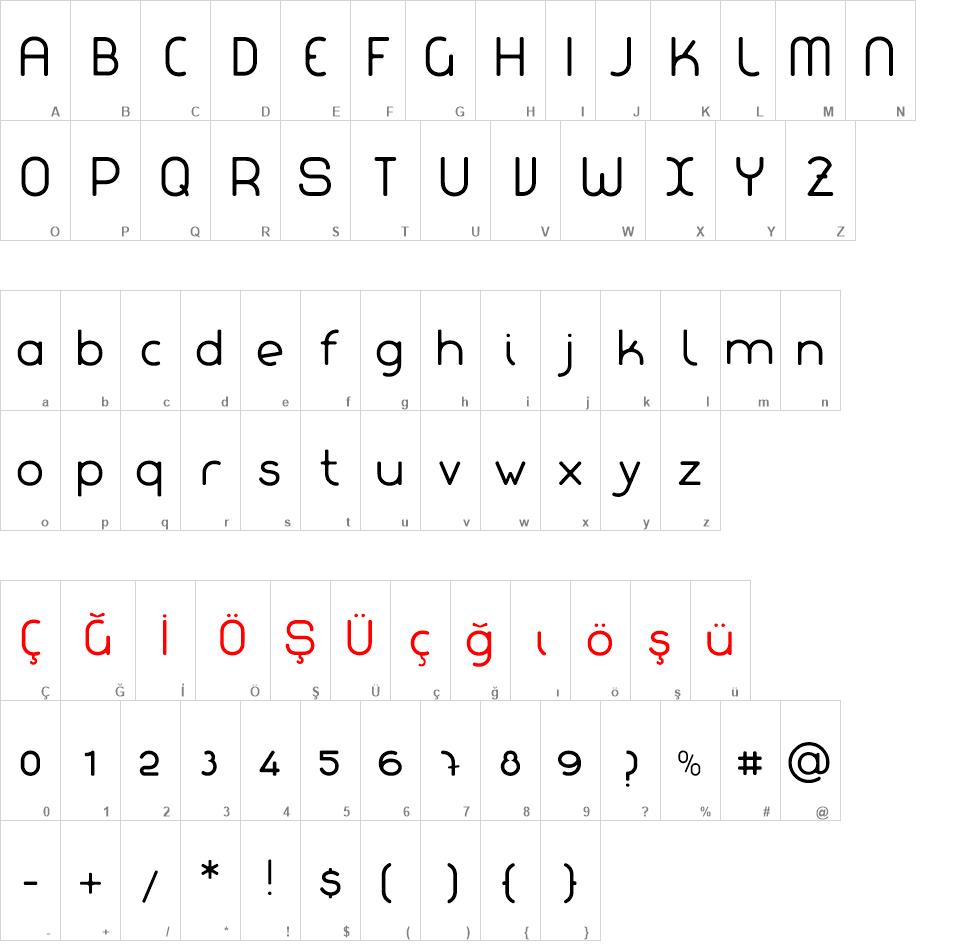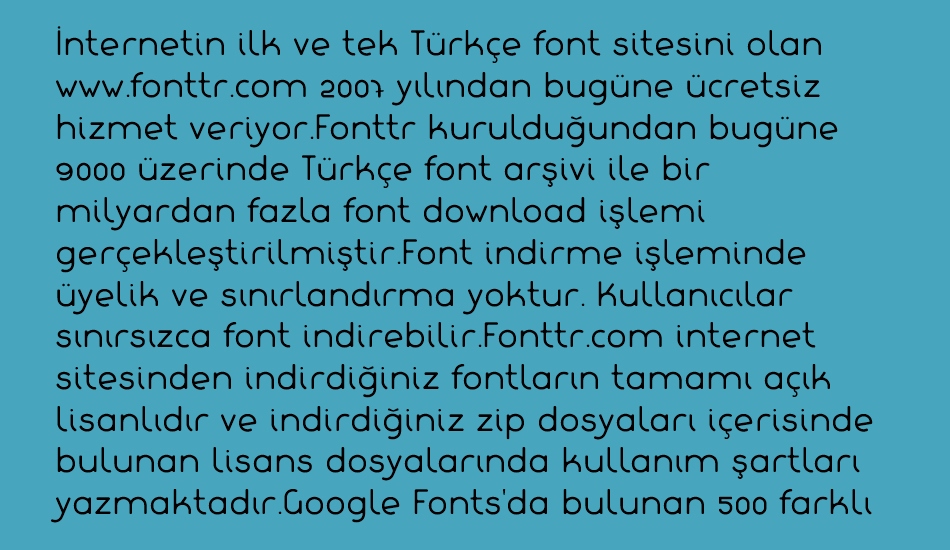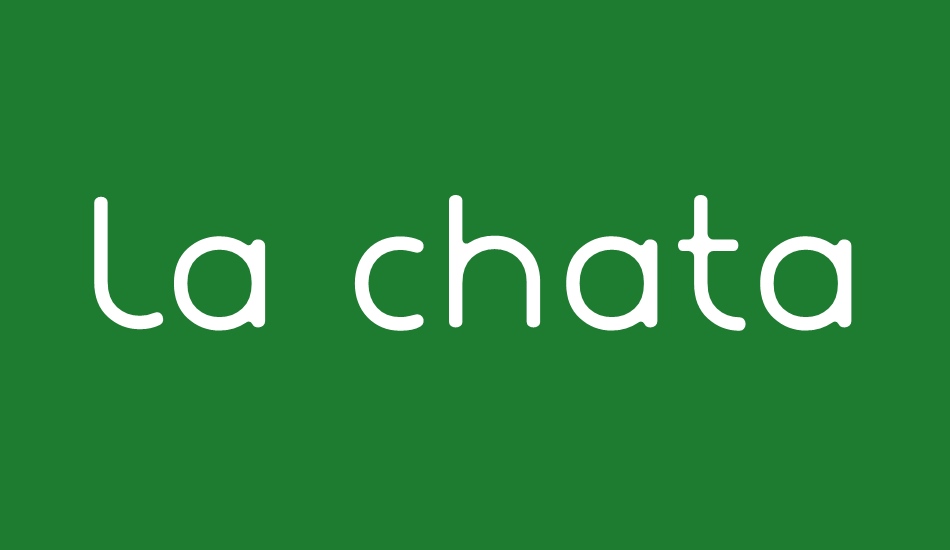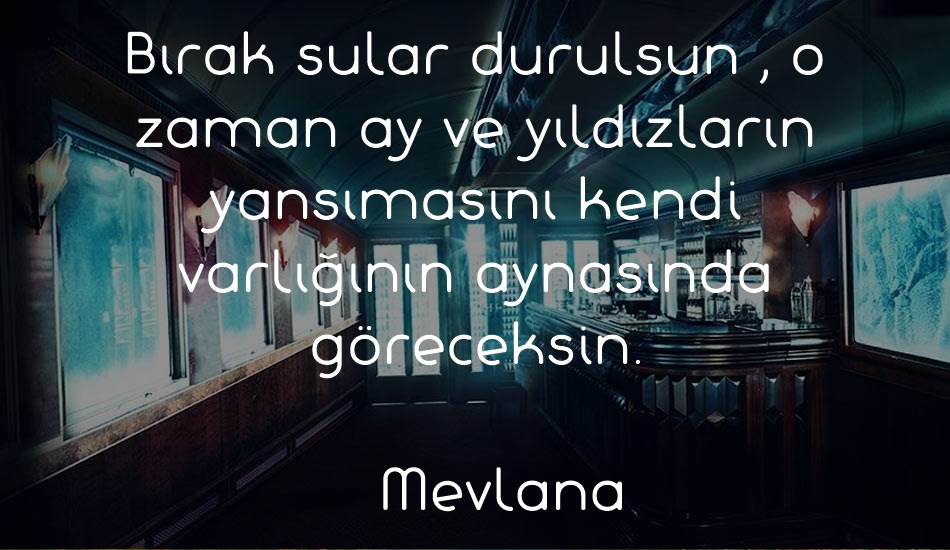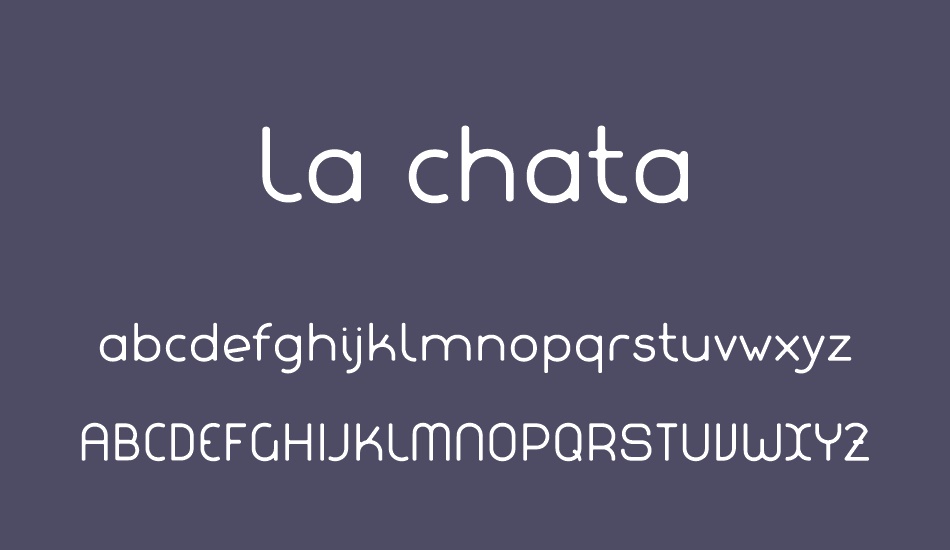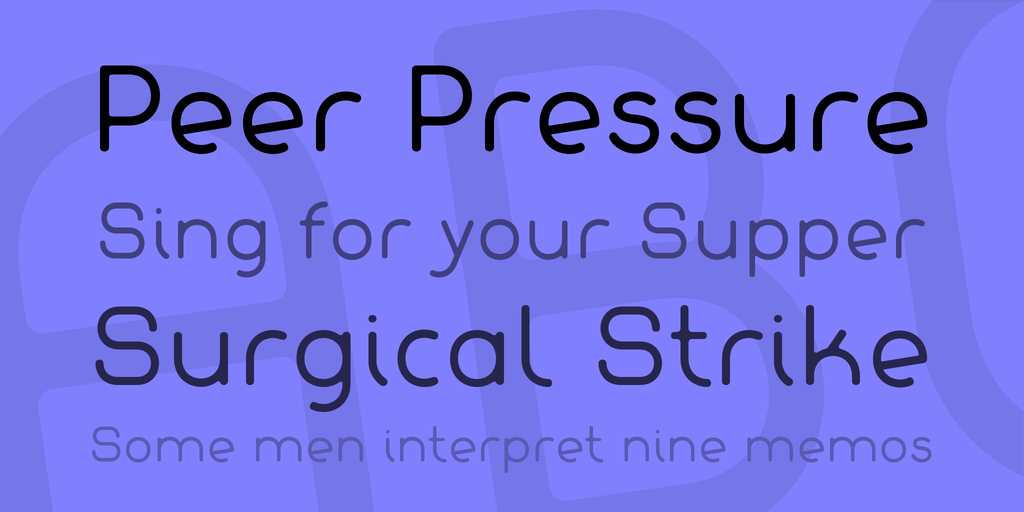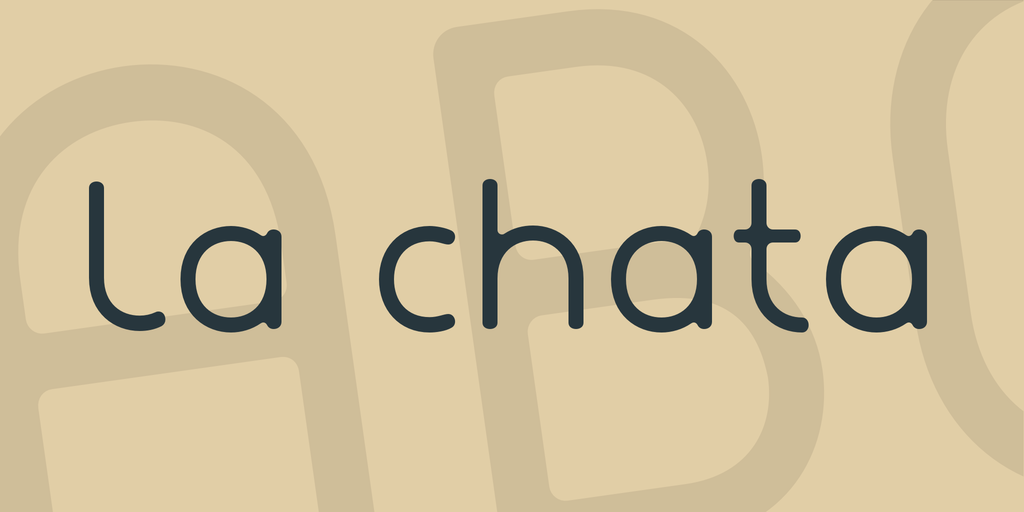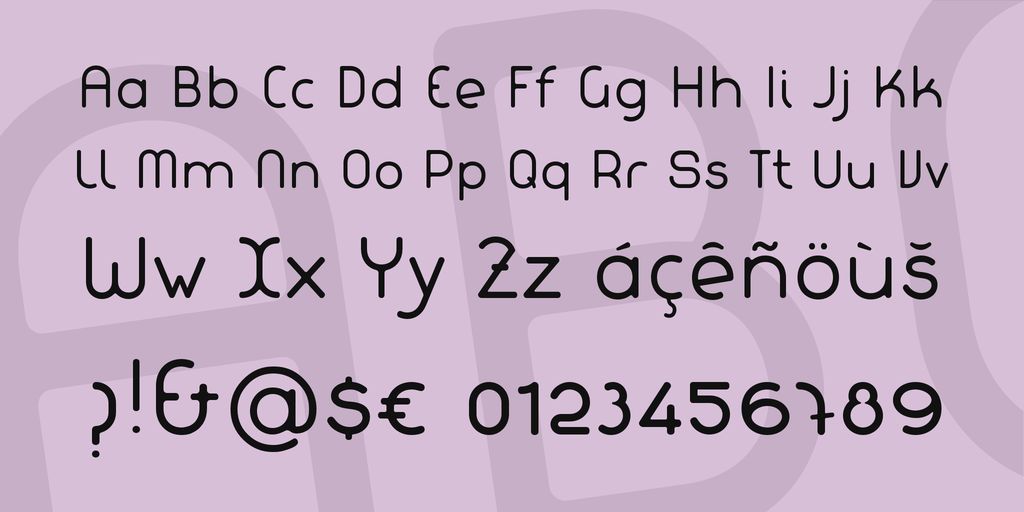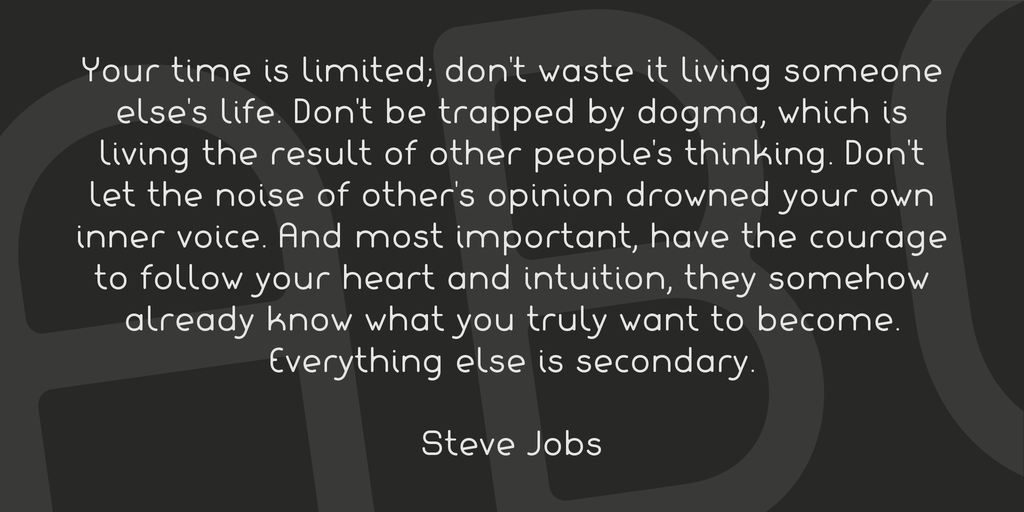
La Chata Font font
La chata font
La Chata Font font
El dise?o de esta fuente surgi? de las 7 letras de mi marca (defharo), dibujadas originalmente en el 2011 con motivo del redise?o de mi logotipo.
The design of this font came from the 7 letters of my brand (defharo), originally drawn in 2011 to mark the redesign of my logo.